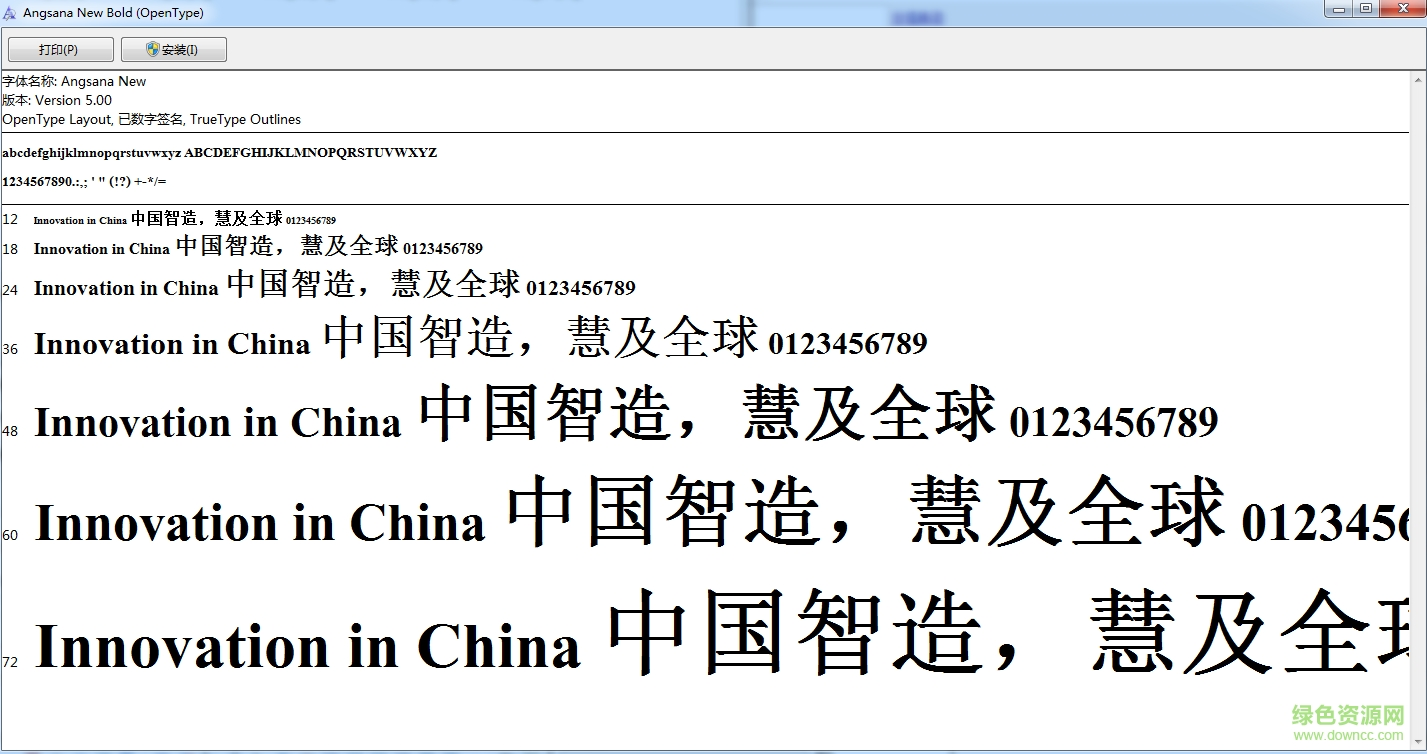
angsana new 粗體
拉丁文的字體種類很多,通常人們根據(jù)字體的發(fā)展和特點(diǎn)分類。拉丁字母字體一般按體系分,每一體系中又有許多體式。體系分為羅馬體體系、哥特體體系、埃及體體系、無(wú)飾線體體系、手寫體體系、裝飾體體系、圖形體體系。每種體系里各自又有一些字體。
angsana new bold
Bold——粗體,Italic——斜體,Light——細(xì)體,Extra——特級(jí),Demi——一半,Medium——中等,Black——加黑,Condensed——縮小體,Expanded——擴(kuò)大,等等